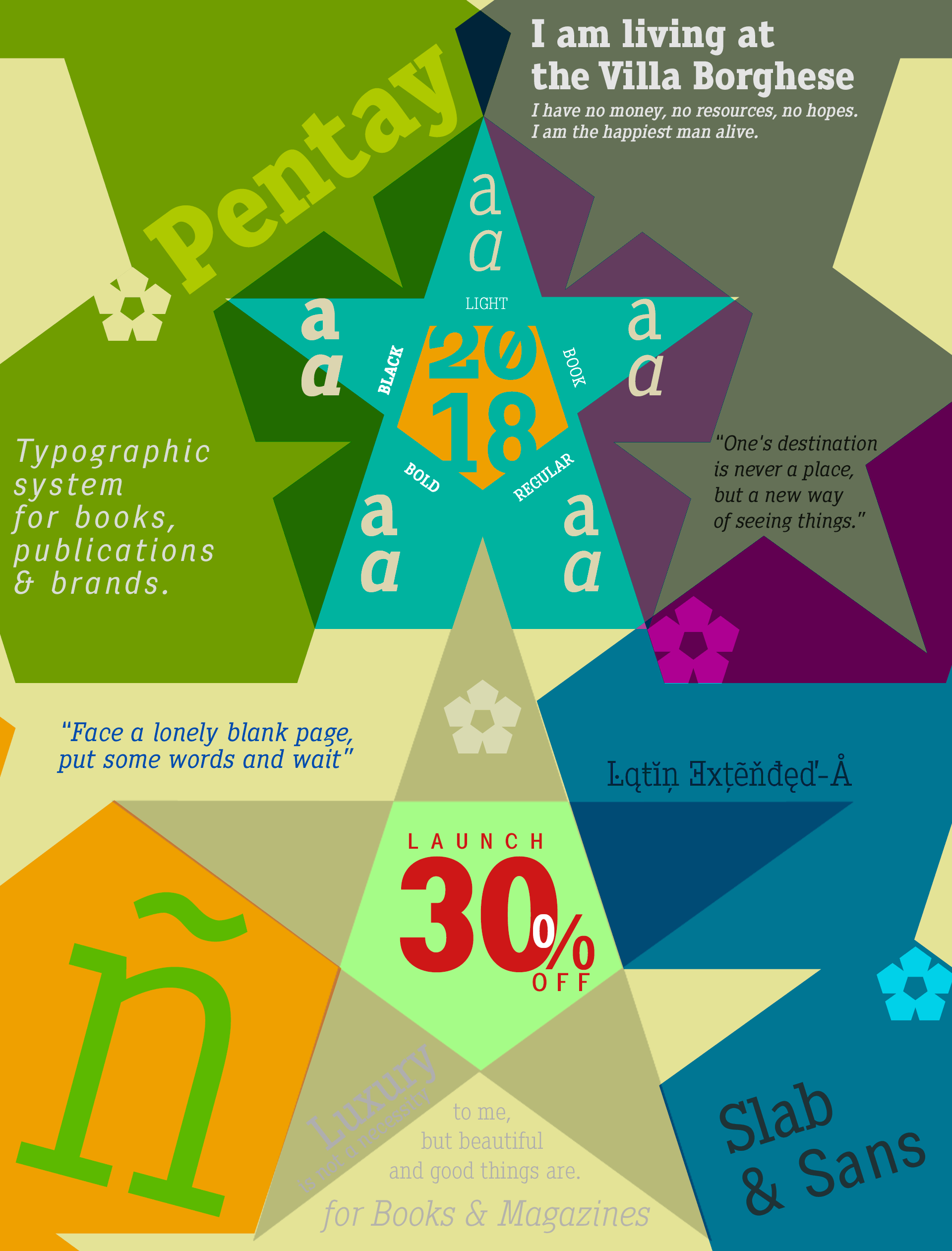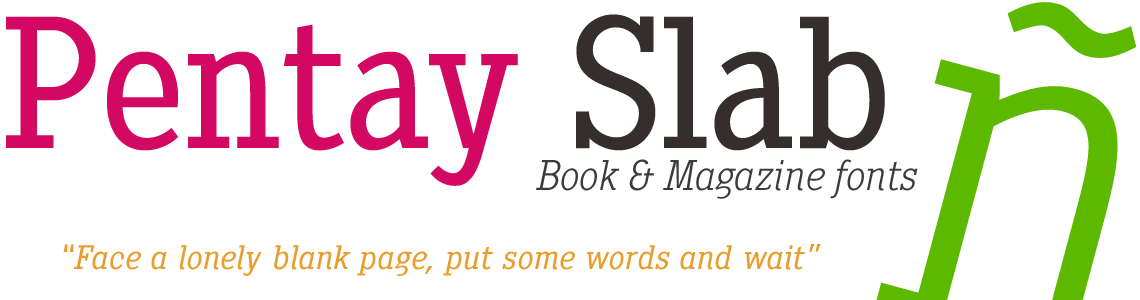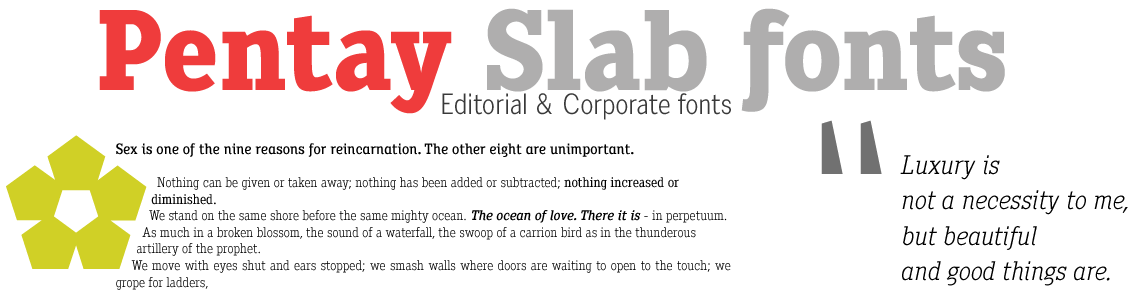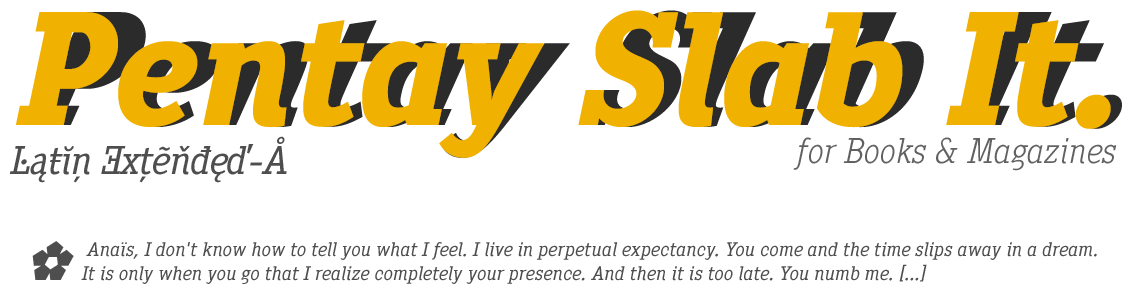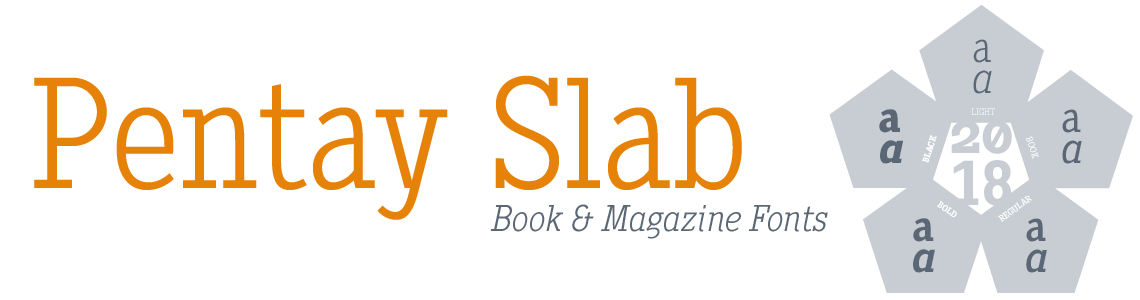
Estilo: Slab Serif, Geométrica, Corporativa
Proporción: Light, Book, Regular, Bold & Black + Italics
Glyphs: 529
Funciones OpenType: Additional languages, All Alternates, Alternate Annotation Forms, Capital Spacing, Denominators, Discretionary Ligatures, Extended Fractions, Historical Forms, Historical Ligatures, Inferiors, Kerning, Localized Forms, Numerators, Oldstyle Figures, Ordinals, Scientific Inferiors, Slashed Zero, Standard Ligatures, Subscript, Superior letters, Superiors, Superscript.
Latin Extended-A & OpenType Features
Las fuentes disponen además de un juego completo de minúsculas alternativas y otros caracteres con funciones avanzadas OpenType.
Las fuentes Pentay disponen en su versión comercial de un juego de 529 glifos (Latin Extended-A), con soporte para cualquier idioma europeo o centro europeo. Pentay Slab también incluye funciones OpenType (Compatibles con InDesign, QuarkXpress, Photoshop e Illustrator.